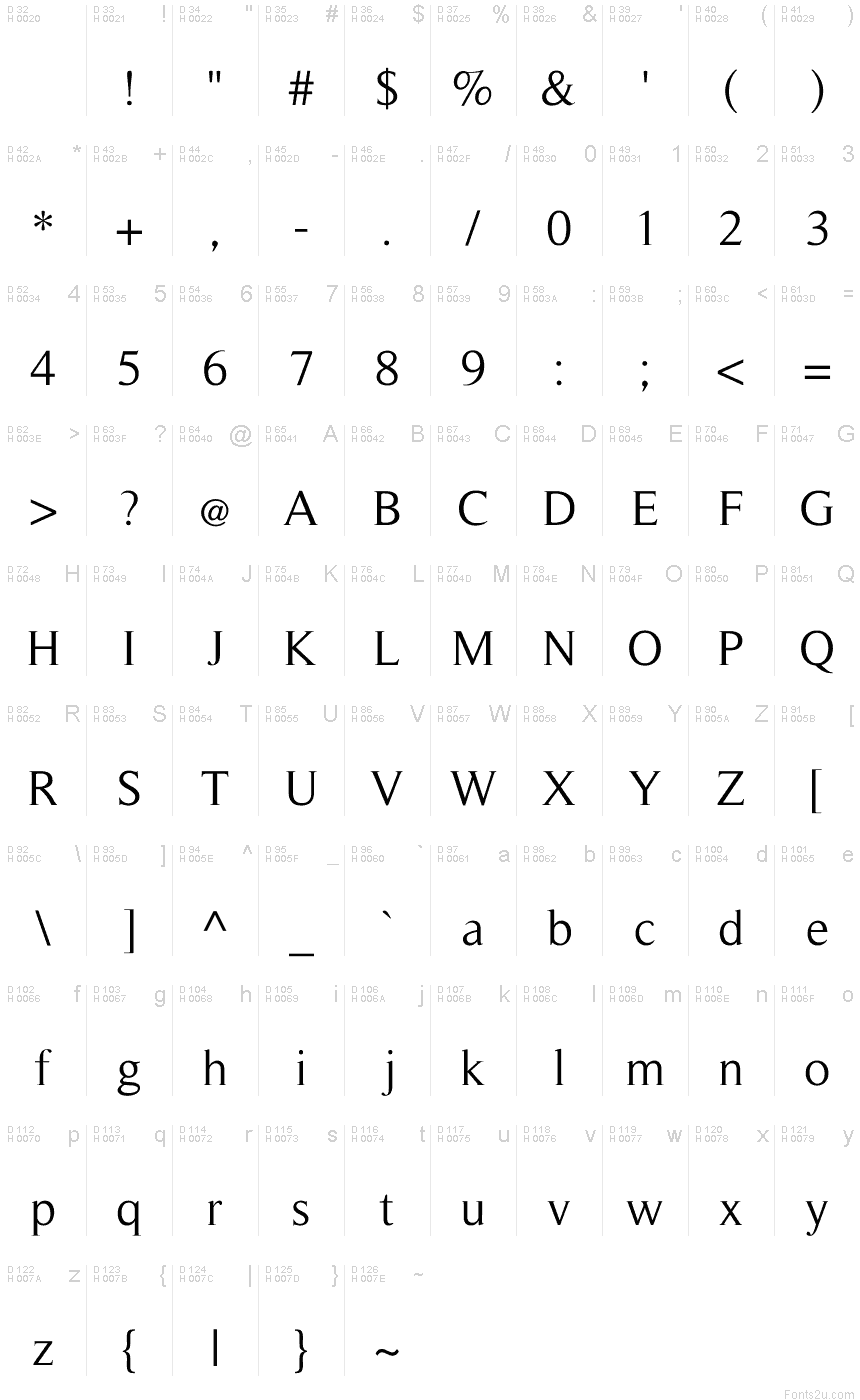
Timeless-Normal
Timeless autorstwa M. Kleina z Fonteria to klasyczny krój szeryfowy o literackim, tradycyjnym charakterze. Litery emanują spokojem i znajomą estetyką, łącząc wysokie, dystyngowane wielkie litery z miękkimi krzywiznami i wyrazistymi szeryfami, które nadają tekstowi stonowany, formalny rytm.
Krój ten doskonale sprawdzi się w projektach wydawniczych, na okładkach książek, w broszurach, na zaproszeniach i tytułach, gdzie pożądana jest tradycja bez zbędnego przepychu. Jako darmowy font, świetnie nadaje się również do cytatów, otwarć rozdziałów i krótkich nagłówków na stronach www, ponieważ wyrafinowany kontrast i pełne kształty sprawiają, że nawet kilka słów wygląda elegancko i przemyślanie.